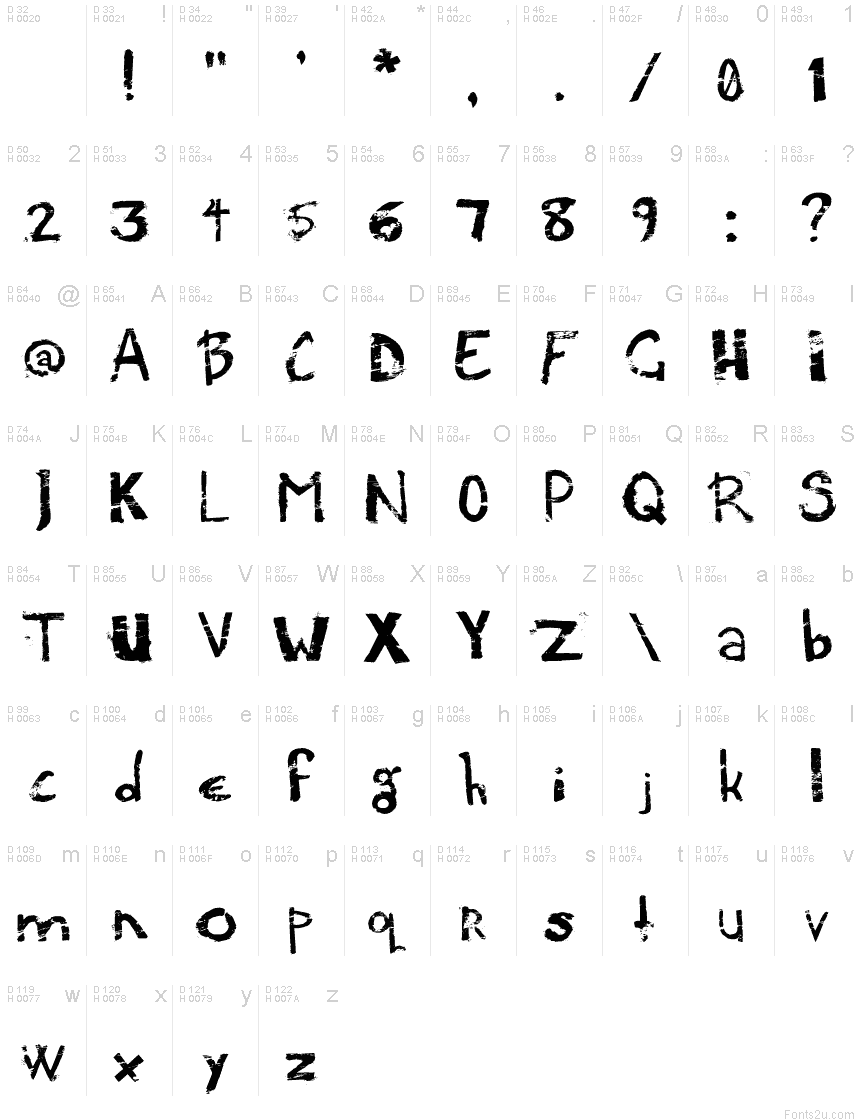
Potato Press to darmowy font pędzlowy z 2005 roku, zbudowany na teksturze suchego pędzla z szorstkimi, poszarpanymi krawędziami. Litery sprawiają wrażenie ręcznie odbitych i nieco sfatygowanych, o masywnych, zaokrąglonych kształtach, które przecinają smugi i prześwity, nadając całości surowy, a nie wygładzony charakter.
Pasuje na plakaty, zin-y, okładki płyt, opakowania i branding kawiarni, gdzie szukasz efektu bardziej „wsiąkniętego w papier” niż wypolerowanego. Jako darmowy font sprawdzi się też w krótkich nagłówkach, tytułach i wyrazistych cytatach – zużyte ślady pędzla nadają nawet prostym słowom dosadny, ręczny wyraz.